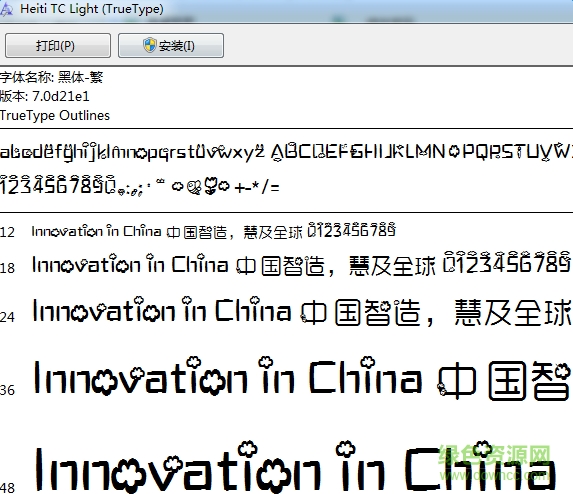
雪花情雨深個(gè)性字體
雪花情雨深字體是一款超好用的中文個(gè)性字體,字體中穿插有各種天氣符號在里面,讓整體的效果看起來更Q萌可愛,喜歡的用戶就趕快來綠色資源網(wǎng)免費(fèi)下載收藏吧!
雪花情雨深字體是一款極具個(gè)性的字體,該字體十分飄逸,彰顯了自己的個(gè)性,有喜歡的朋友可以來綠色資源網(wǎng)下載使用!